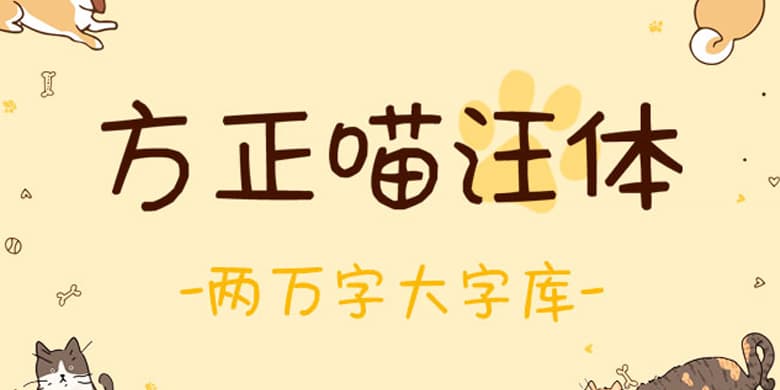
品牌:方正手迹设计师:宋昱东发行时间:2020字库编码:简繁扩展(GBK)分类:创意书写字体属性:精品字
方正喵汪体是一款卡通风格的创意手写字体,将字体中所有的口字形简化为手绘的圆圈,所有的转折也做圆弧处理,显得简单可爱。中宫略大,增加字面,结构多变的同时又保持重心不变,具有良好的展示效果。不但适用于儿童类的书刊、品牌广告和产品包装设计,以及社交网络的个性化用字,还可胜任简短的正文排版。